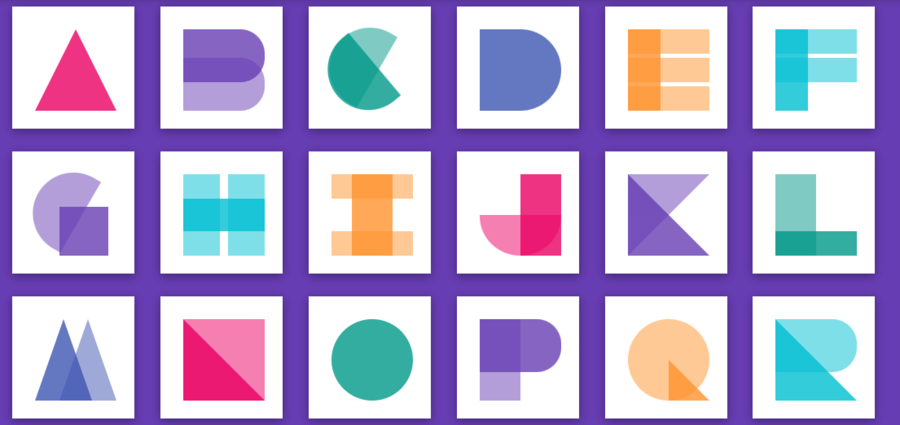
Maîtrisez l'Art de la Typographie : Jeux ludiques pour Intégrateurs
Aujourd'hui, je vous propose une liste d'inspiration faisant la part belle aux textes et typographies.
Il ne faut pas l'oublier, le web, c'est avant tout du texte (et des vidéos de chatons, mais j'ai choisi de passer ce sujet sous silence). Cette liste d'inspirations met donc en avant des créations en HTML/CSS centrées sur les typographies, le texte et son utilisation de manière détournée.
Celle liste vous propose donc en vrac deux polices uniquement en CSS (donc le lien juste en dessous, avec une police material design du plus bel effet), une font en PNG très intéressante de par sa construction, et un pattern composé de lettres, qui permettrait des interactions très intéressantes. Petit coup de coeur pour l'horloge en full-texte, que j'aime toujours autant.
Jeux typographiques